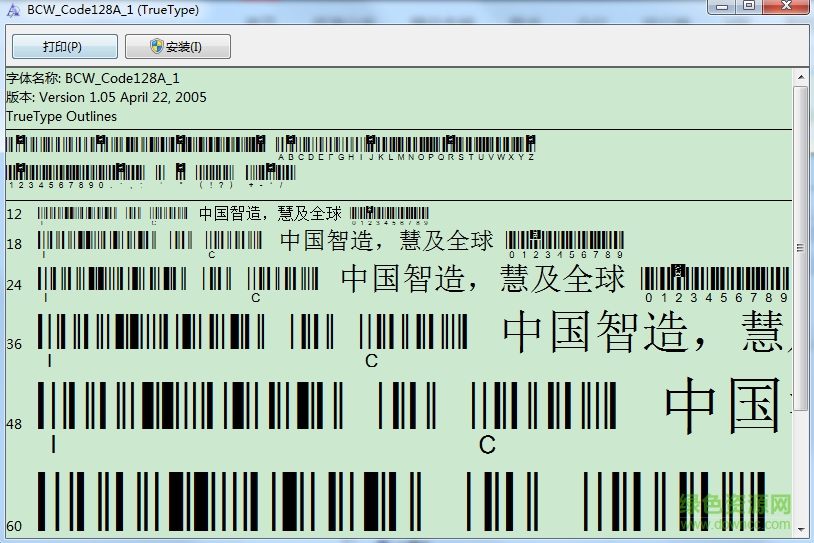
CODE128a是一款常用的條碼字體,這款條碼字體設(shè)計(jì)的比較美觀,應(yīng)用非常的廣泛,能夠完美支持阿拉伯文、標(biāo)點(diǎn)符號(hào)等,需要的這款字體的朋友歡迎來(lái)綠色資源網(wǎng)免費(fèi)下載使用。
CODE128碼是廣泛應(yīng)用在企業(yè)內(nèi)部管理、生產(chǎn)流程、物流控制系統(tǒng)方面的條碼碼制,由于其優(yōu)良的特性在管理信息系統(tǒng)的設(shè)計(jì)中被廣泛使用,CODE128碼是應(yīng)用最廣泛的條碼碼制之一。
●可表示高密度數(shù)據(jù)和字符串;
●每個(gè)字符由3個(gè)條、3個(gè)空、11個(gè)單元構(gòu)成,字符串可變長(zhǎng);
●符號(hào)內(nèi)含校驗(yàn)碼;
●有三種不同的版本:A(數(shù)字、大寫(xiě)字母、控制字符)B(數(shù)字、大小字母、字符)C(雙位數(shù)字)
CODE128A:標(biāo)準(zhǔn)數(shù)字和大寫(xiě)字母,控制符,特殊字符
CODE128B:標(biāo)準(zhǔn)數(shù)字和大寫(xiě)字母,小寫(xiě)字母,特殊字符
CODE128C:[00]-[99]的數(shù)字對(duì)集合,共100個(gè)
●可用128個(gè)字符分別在A、B或C三個(gè)字符串集合中。